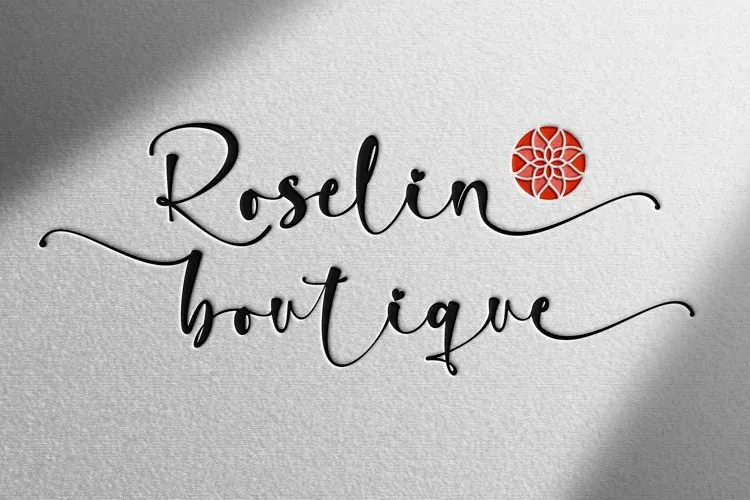
Rossellia Font
Esta fonte foi criada por Stefani Letter, oferecendo uma experiência visual delicada e elegante. A Rossellia Font é um tipo de escrita feito à mão que transmite modernidade e sofisticação com um estilo inspirado na calligrafia. Cada letra possui seu próprio toque único e belo, tornando sua ideia ou design ainda mais vívidos! As linhas suaves e os elementos gráficos deslumbrantes fazem dela uma escolha incrível para designers que procuram dar vida a seus projetos. Além disso, é PUA codificado, permitindo a fácil acessibilidade de todos os incríveis caracteres e swashes. Ela ainda oferece uma ampla variedade de recursos especiais, como alternativas de letras e ligaturas. Esta fonte não apenas traz um toque singular à sua obra, mas também eleva-a ao próximo nível, destacando seus melhores pontos através da sua elegância e sofisticação inigualáveis. Ideal para aqueles que buscam uma fonte de escrita feita à mão perfeita para expressar seus ideais em design.